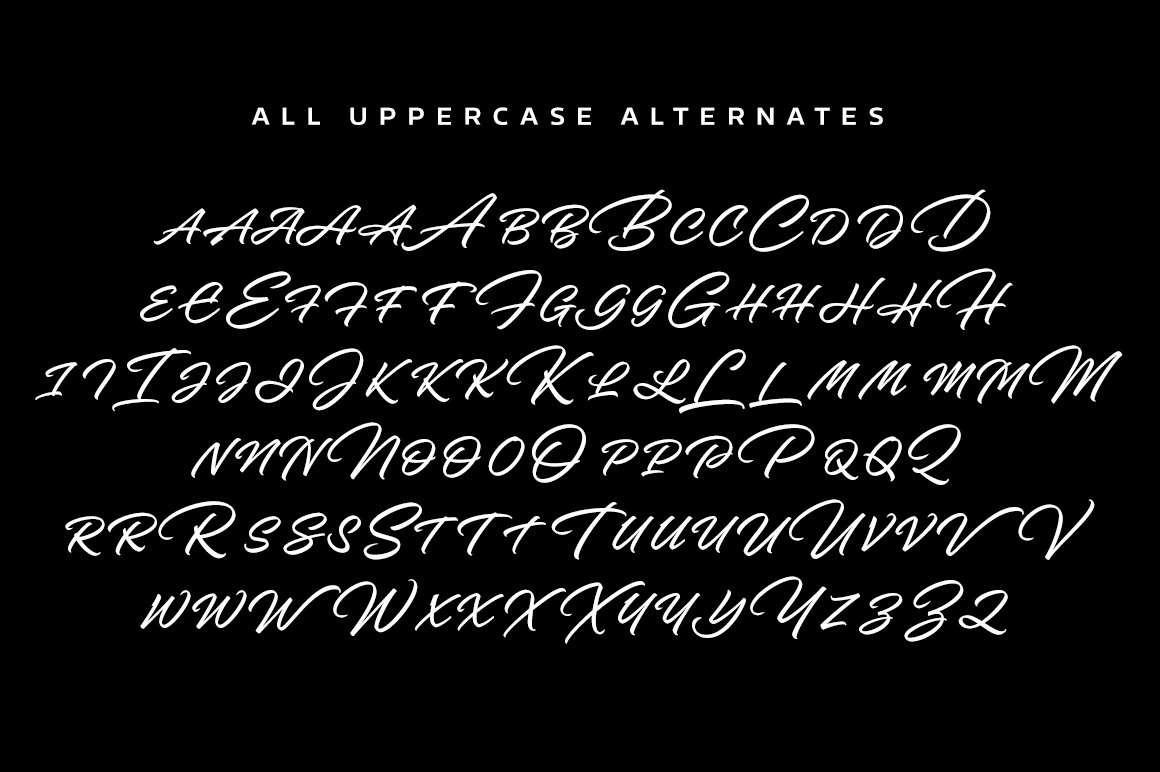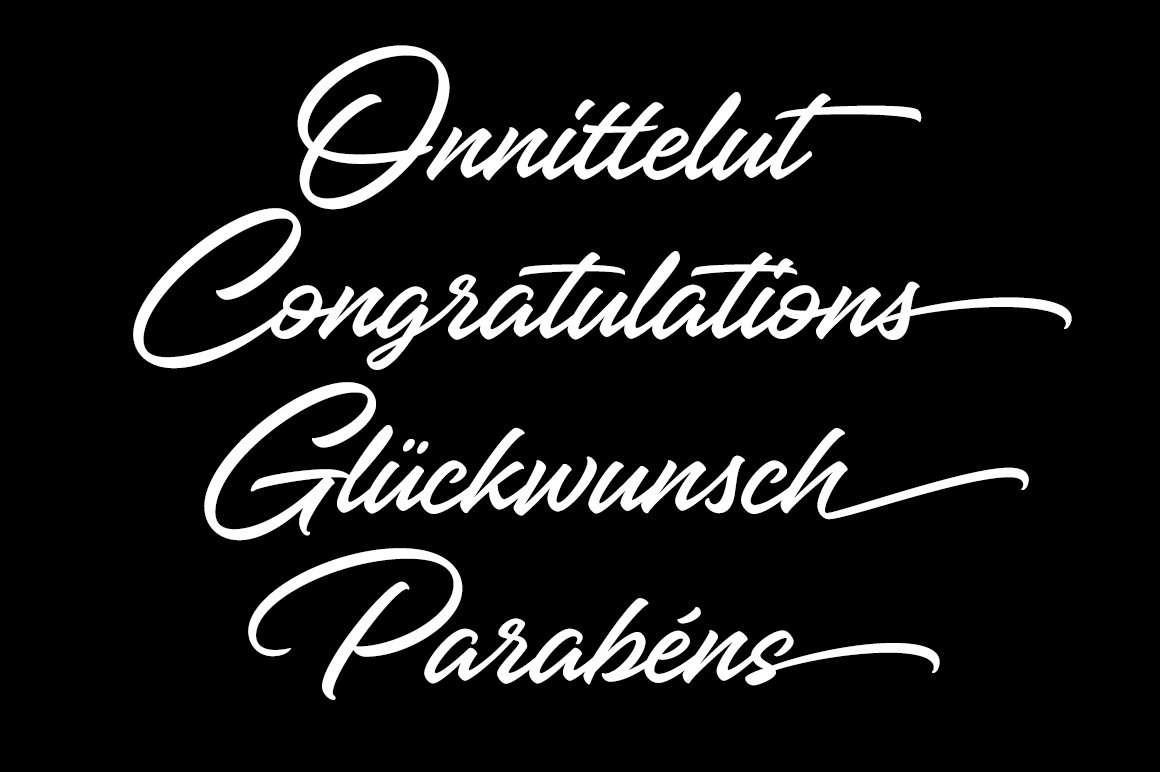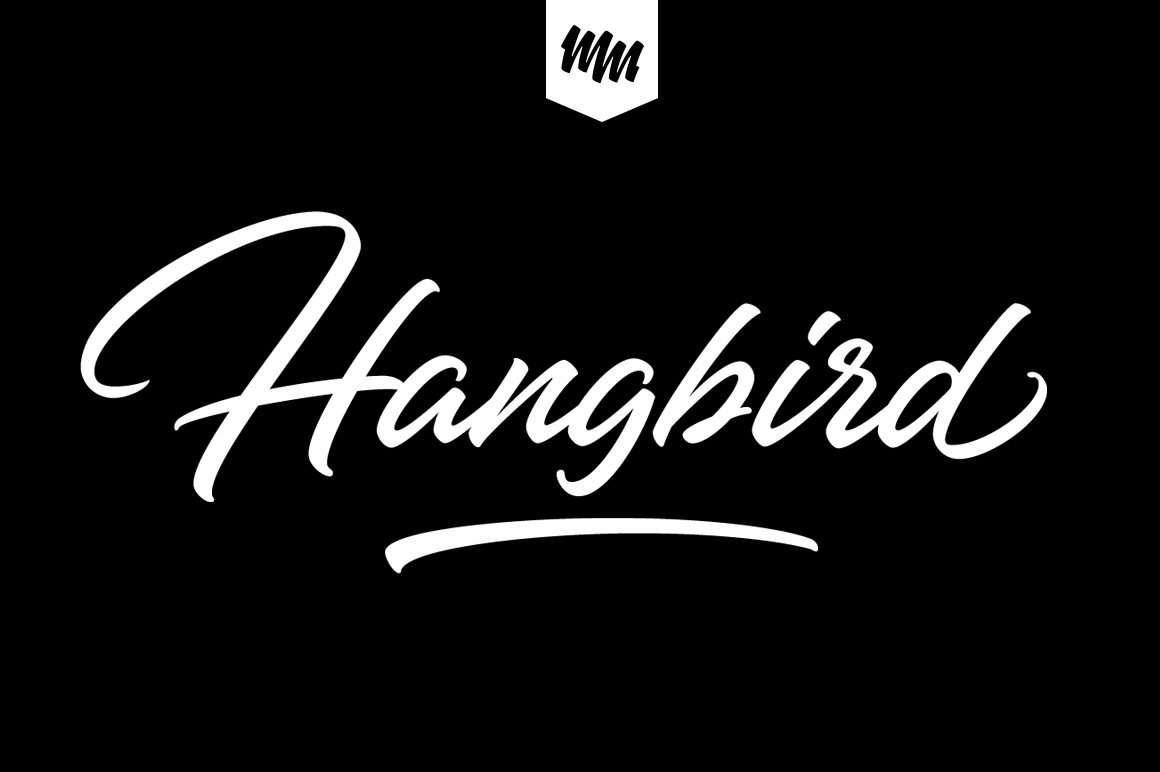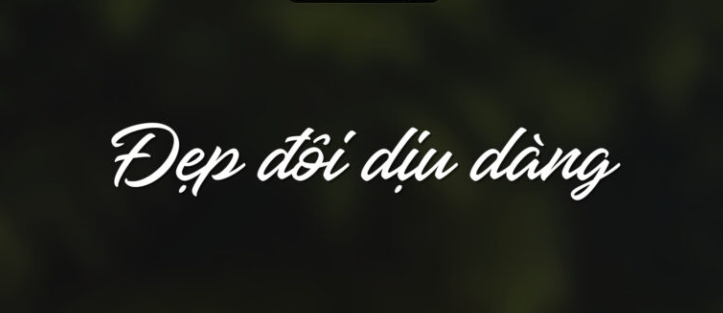
MTD Hangbird là bộ phông chữ thuộc dòng Script mang phong cách vẽ bảng hiệu cổ điển (Sign-painter Script), nổi bật với những đường nét uốn lượn dày dặn, phóng khoáng và tràn đầy năng lượng tự tin. Được sáng tạo ban đầu bởi nhà thiết kế danh tiếng Mika Melvas và được đội ngũ MTD tinh chỉnh hoàn thiện hệ thống dấu tiếng Việt, Hangbird là lựa chọn hoàn mỹ cho các thiết kế logo quán cà phê phong cách Retro, nhãn bia thủ công, bao bì đồ ăn nhanh và thời trang Streetwear cá tính. Doozypack.vn cung cấp link tải Font MTD Hangbird Việt hóa chuẩn kỹ thuật, giúp bạn sở hữu phông chữ đậm chất hoài cổ mà không lo gặp bất kỳ lỗi hiển thị dấu thanh nào khi thiết kế in ấn.
Đặc điểm thẩm mỹ độc đáo của bộ font MTD Hangbird
Hangbird tái hiện trọn vẹn tinh thần phóng khoáng của nghệ thuật vẽ chữ thủ công thế kỷ 20, nơi từng nét cọ đều chứa đựng sự dứt khoát và nhịp điệu đồ họa lôi cuốn.
Phong cách Sign-painter Script cổ điển và phóng khoáng
Đặc trưng lớn nhất của MTD Hangbird là cấu trúc nét chữ to bản (bold script) với những mảng mực đặc vững chãi. Cấu trúc chữ có độ nghiêng nhẹ nhàng về phía trước, các góc chuyển nét mềm mại mô phỏng áp lực của đầu bút lông dẹt trên bảng gỗ. Phong cách này mang lại sự ấm áp, mộc mạc và đậm đà phong vị vintage, giúp tiêu đề bản thiết kế của bạn ngay lập tức chiếm trọn ánh nhìn của khách hàng từ khoảng cách xa trên kệ hàng.
Cấu trúc chữ đậm đà với những đường nét kết nối tự nhiên
Các ký tự của MTD Hangbird Việt hóa liên kết với nhau bằng những nét lượn sóng nhịp nhàng, tạo nên một dòng chảy văn bản trôi chảy và sống động. Từng con chữ đều sở hữu phần thân đầy đặn, giúp các dòng slogan hay tên thương hiệu toát lên vẻ chững chạc, uy tín và tạo dựng niềm tin vững chắc về tay nghề thủ công của nhà sản xuất.
Ưu điểm nổi bật của bản MTD Hangbird Việt hóa
Khi ứng dụng các phông chữ script nét dày vào thị trường trong nước, sự chỉn chu về dấu câu là yếu tố quyết định đến tính chuyên nghiệp của bản thiết kế:
- Khắc phục triệt để lỗi dấu tiếng Việt: Phiên bản Font Việt hóa MTD Hangbird đã được đội ngũ thiết kế trau chuốt thủ công từng dấu câu. Các dấu sắc, huyền, hỏi, ngã, nặng được vẽ mập mạp, nghiêng đồng điệu cùng thân chữ gốc, không gây cảm giác chắp vá hay làm mất đi tính thẩm mỹ liền mạch.
- Kiểm soát hiện tượng tràn mực (Dot Gain) tại khe chữ nhỏ: Các khe hở bên trong chữ cái của Hangbird (như chữ ‘e’, ‘a’) khá hẹp. Khi in trên giấy có độ thấm mực cao như giấy Kraft, mực có thể bị lan làm bít kín các lỗ hở này. Bạn nên giữ size chữ tiêu đề tối thiểu từ 10pt trở lên để bảo đảm độ sắc nét.